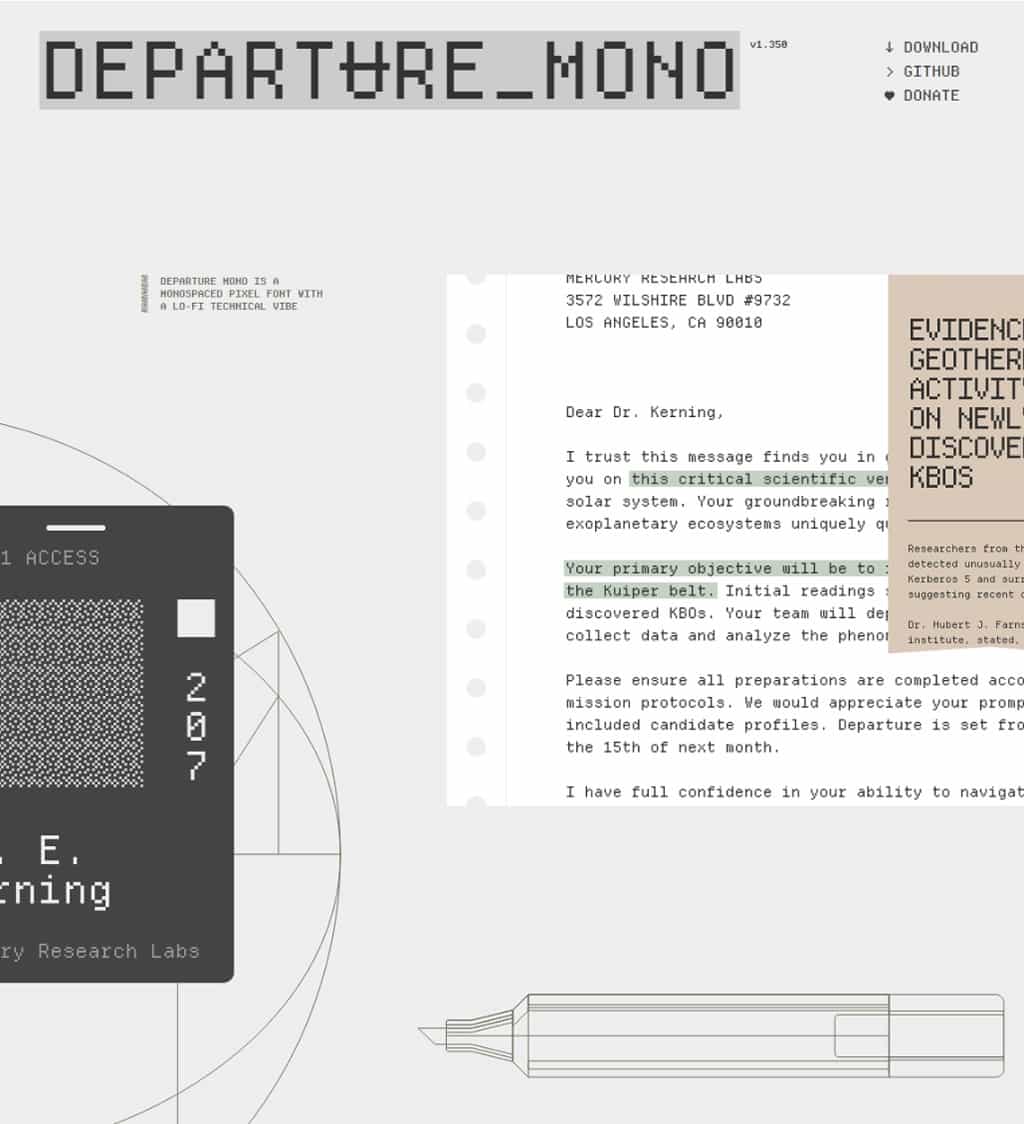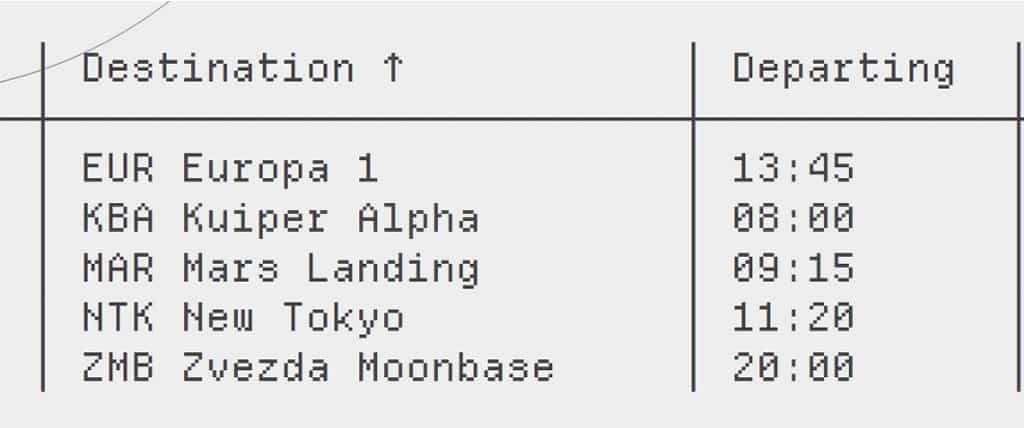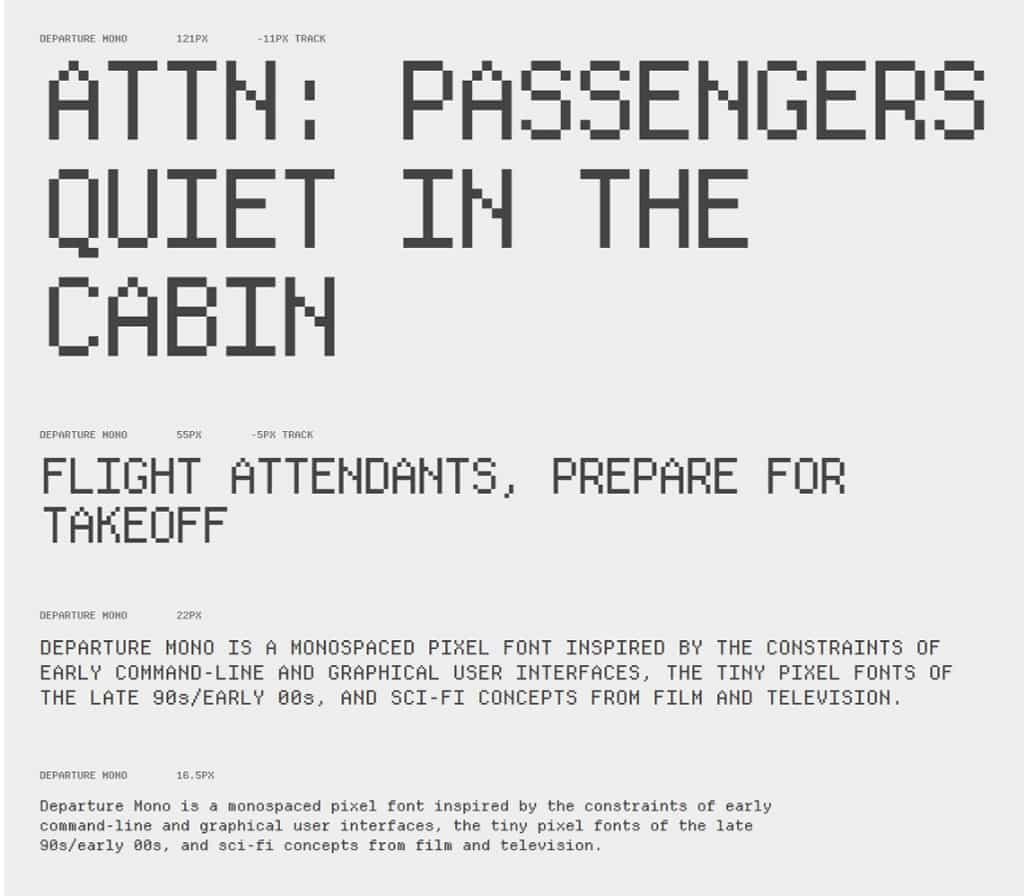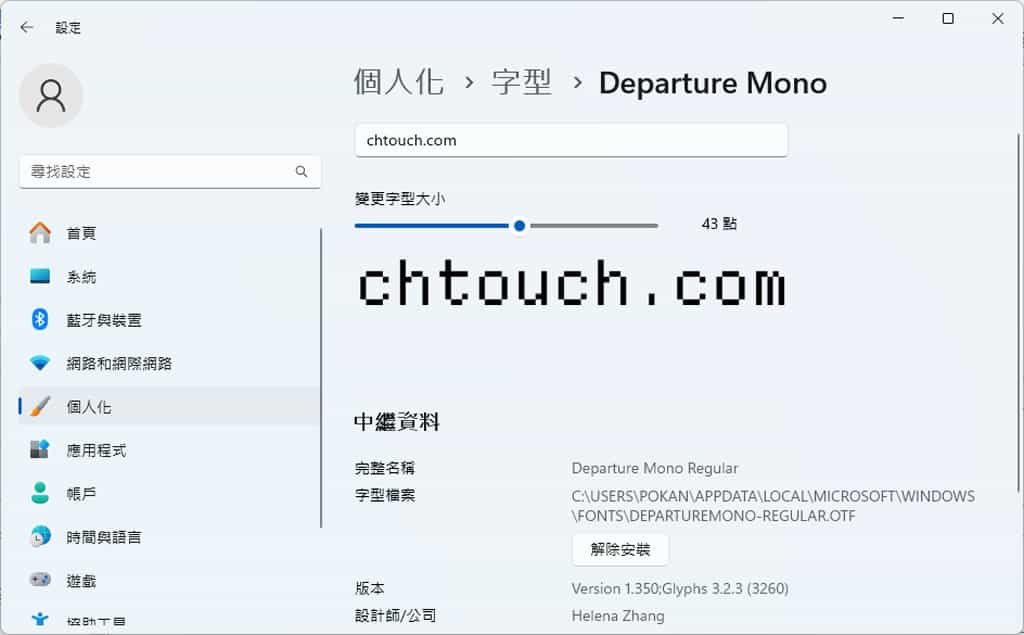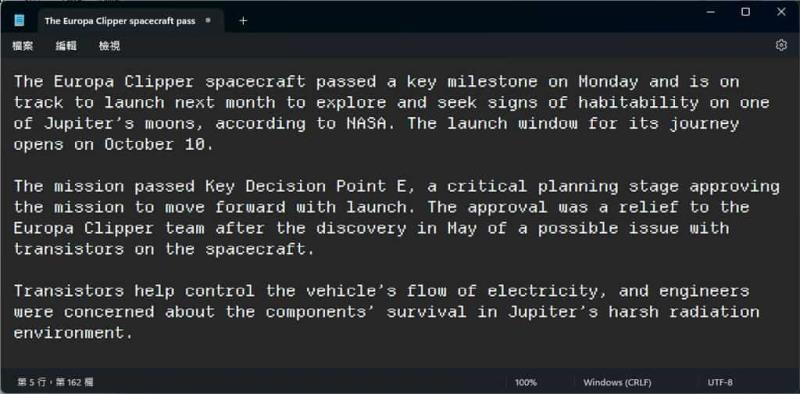
Departure Mono 是一個免費的等寬像素英文字型,其靈感來自早期命令列與圖形使用者介面、90 年代末及 2000 年代初的小型像素字體,以及電影和電視中的科幻概念。等寬字體的優點在於每個字元佔用相同的水平空間,使其在編寫程式、命令列介面及排版設計中,具有更高的可讀性與一致性,特別適合對齊表格、程式碼及其他需要精確對齊的應用場景。此字體採用 SIL 開放字型授權(SIL Open Font License),不僅允許個人免費使用,商業用途嵌入也無限制,唯一的要求是不能單獨出售此字體。Departure Mono 提供多達 775 個字形,涵蓋大小寫英文字母、數字、舊式數字、分數、簡單框線字元以及選定的符號。
靈感來自命令列與科幻設計,適用於程式設計、排版及商業應用
1.等寬字型在應用上特別適合對齊表格、程式碼,以及其他需要精確對齊的場景。網站上也列出了相關的使用情境,供用戶參考,以便更好地運用此字體的優勢與實際用途。
Departure Mono 不僅在設計上具有復古像素風格,還具備等寬字體的實用優勢,非常適合程式設計、排版及其他需要精準對齊的應用場景。加上免費的 SIL 授權,無論是個人還是商業項目,都能無縫地嵌入這個字體,為設計增添專業感與獨特性。